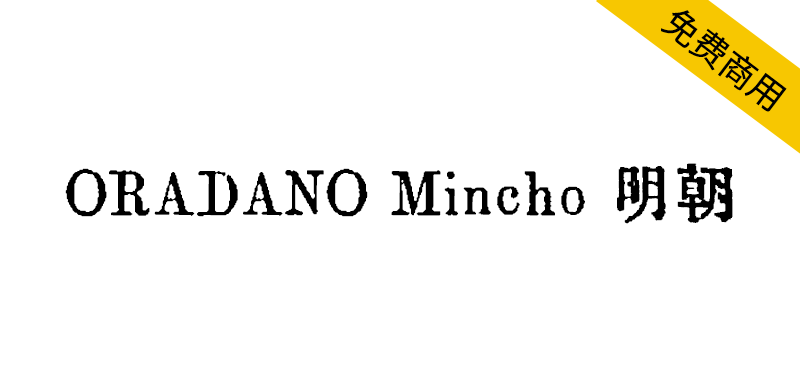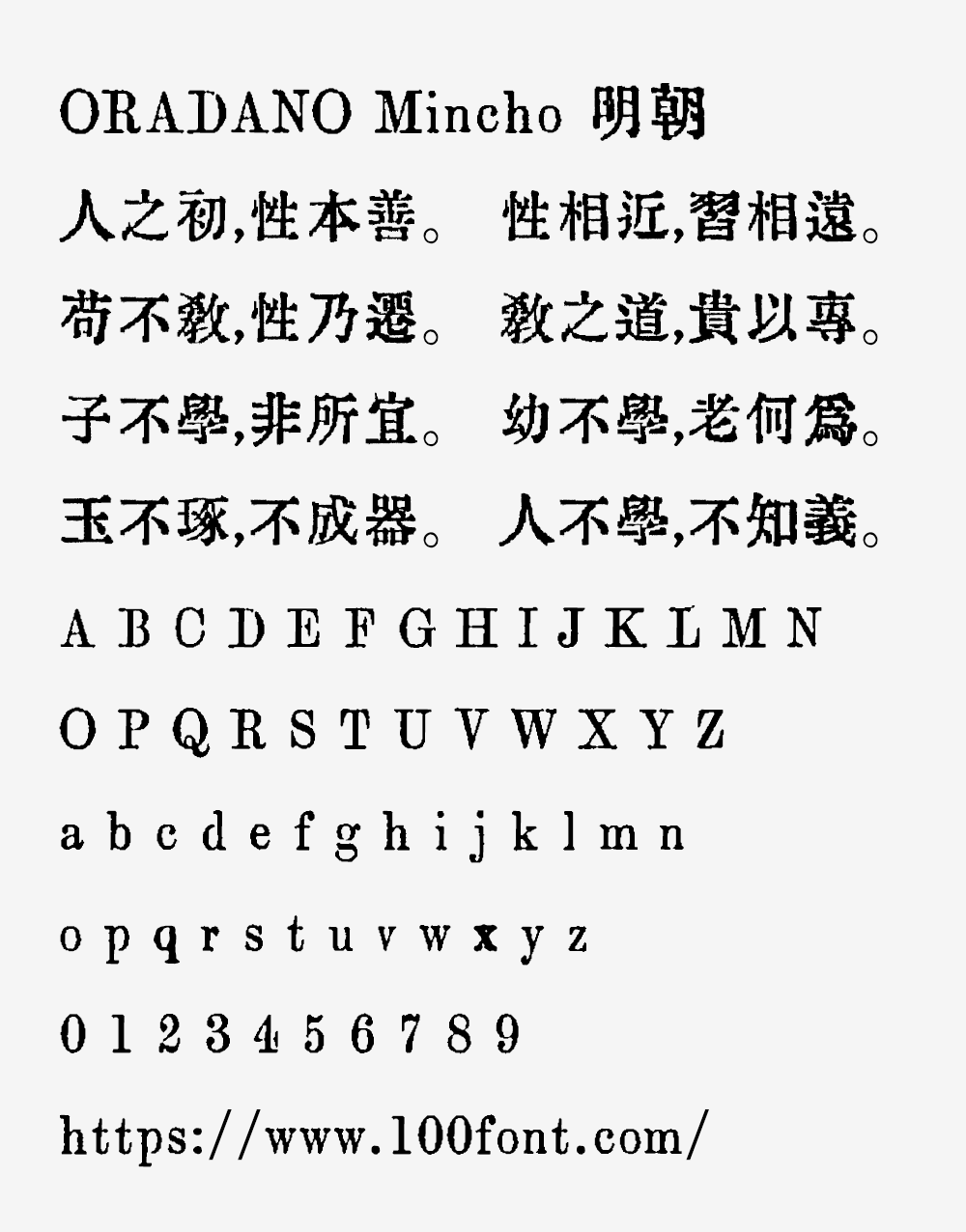
「ORADANO Mincho 明朝」一款日本铅字印刷效果字体,可免费商用,很有味道的一款印刷字体,非常适合用来做平面设计。 2003年第一版后开始持续更新,很有味道的一款印刷字体非常适合用来做平面设计。数十年后今年6月推出第二版,收录非常多的汉字字型,后又追加青空文库使用频率最高的前两千个汉字外,亦收录 1981 年版最常使用汉字字种。
使用Oradano明朝字体/Oradano明朝GSRR字体